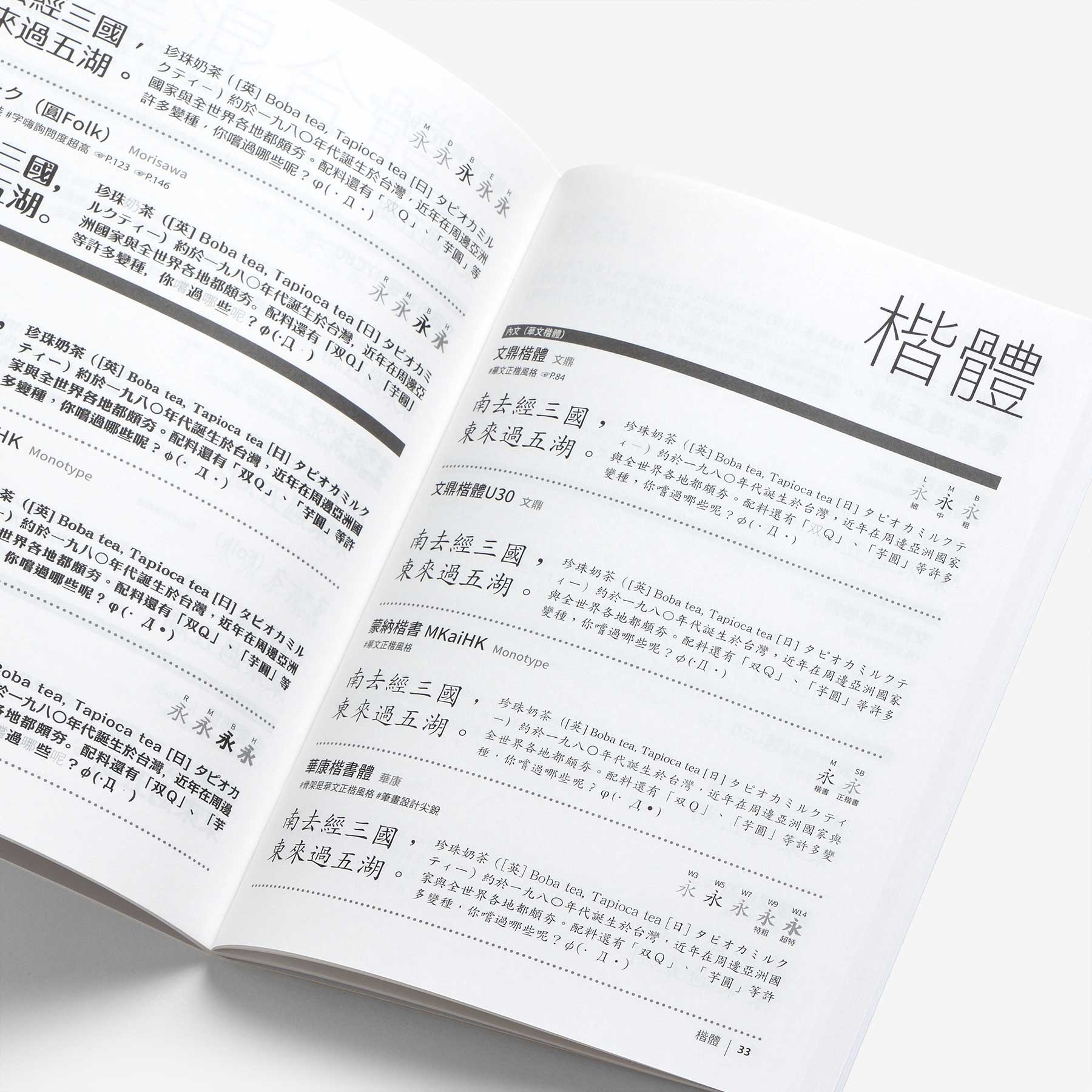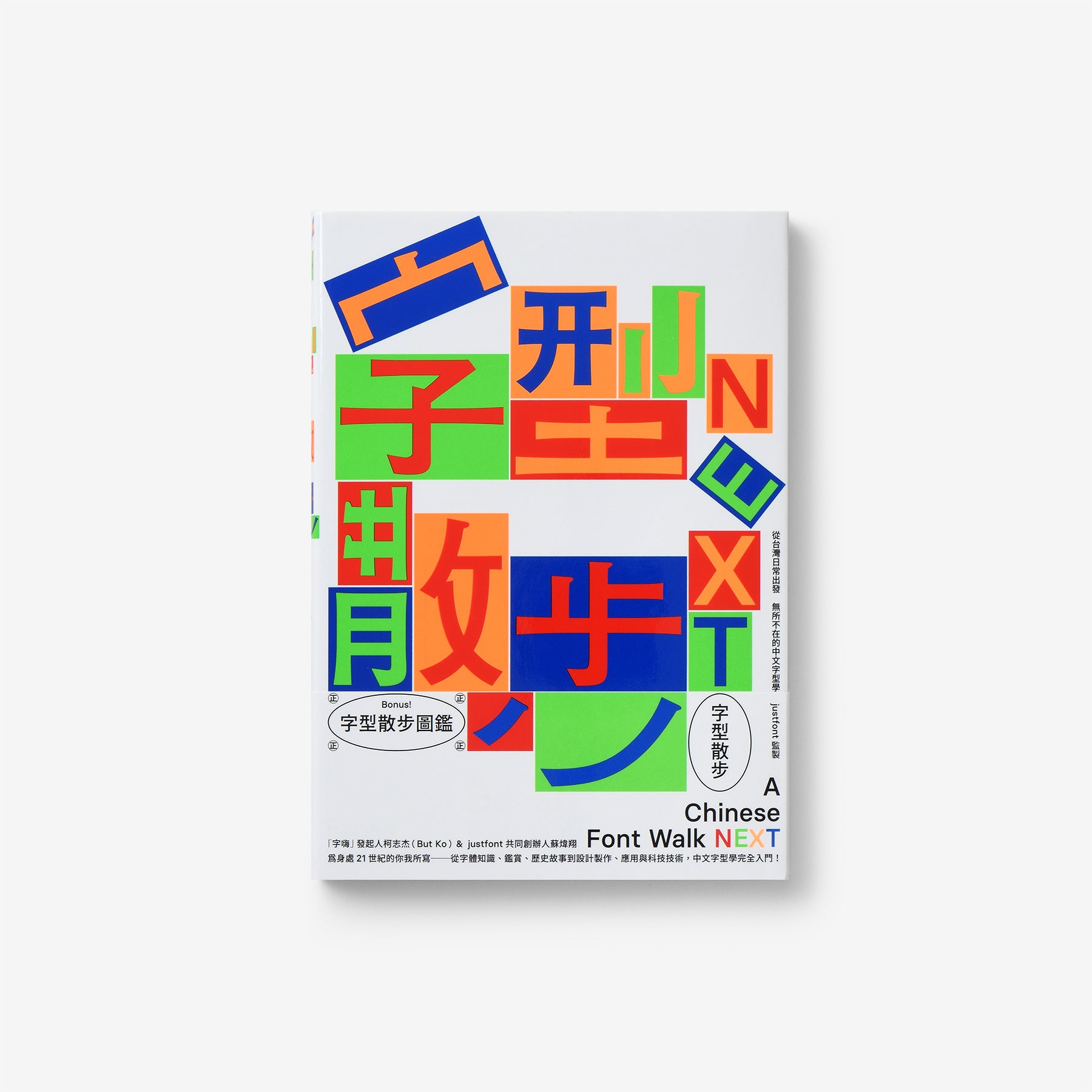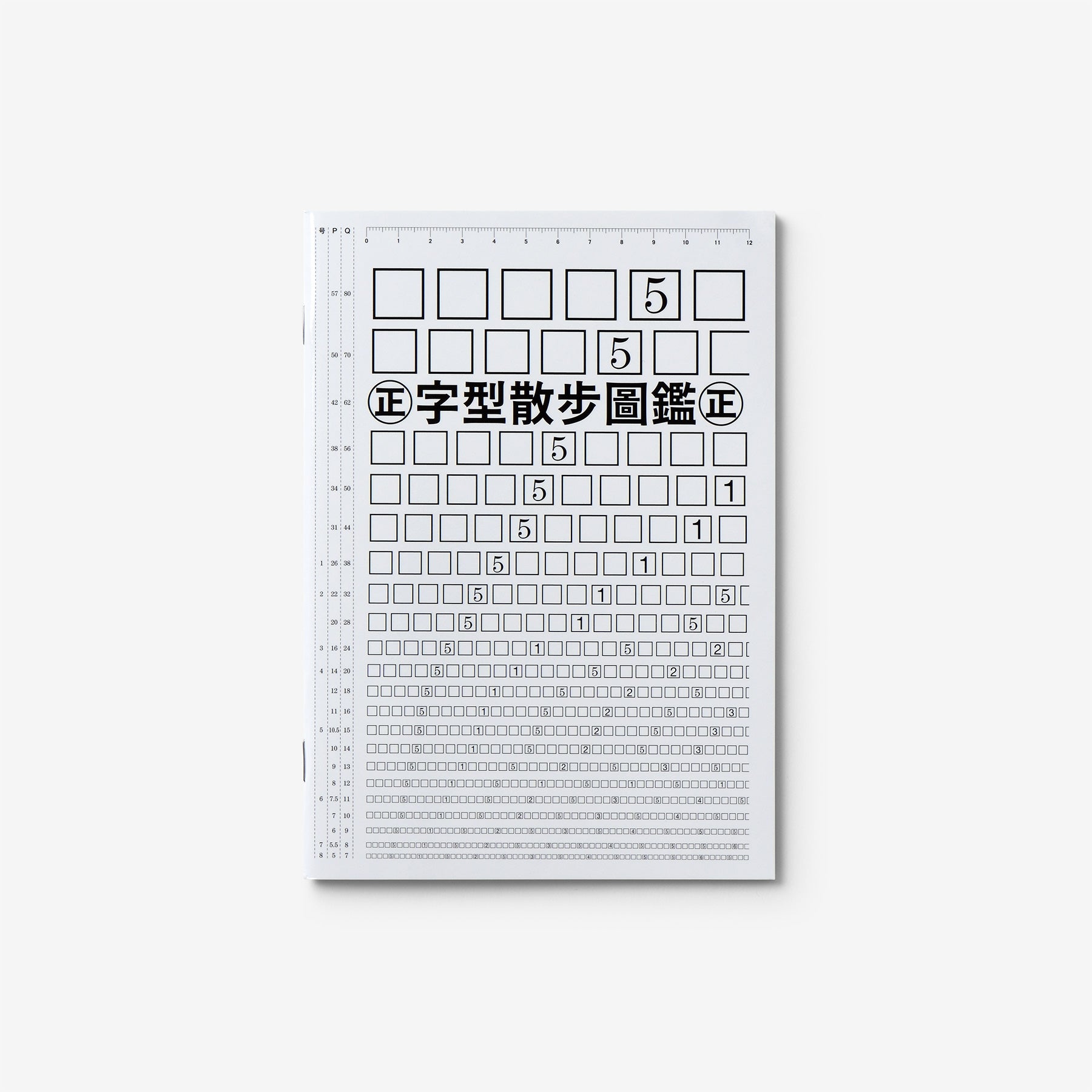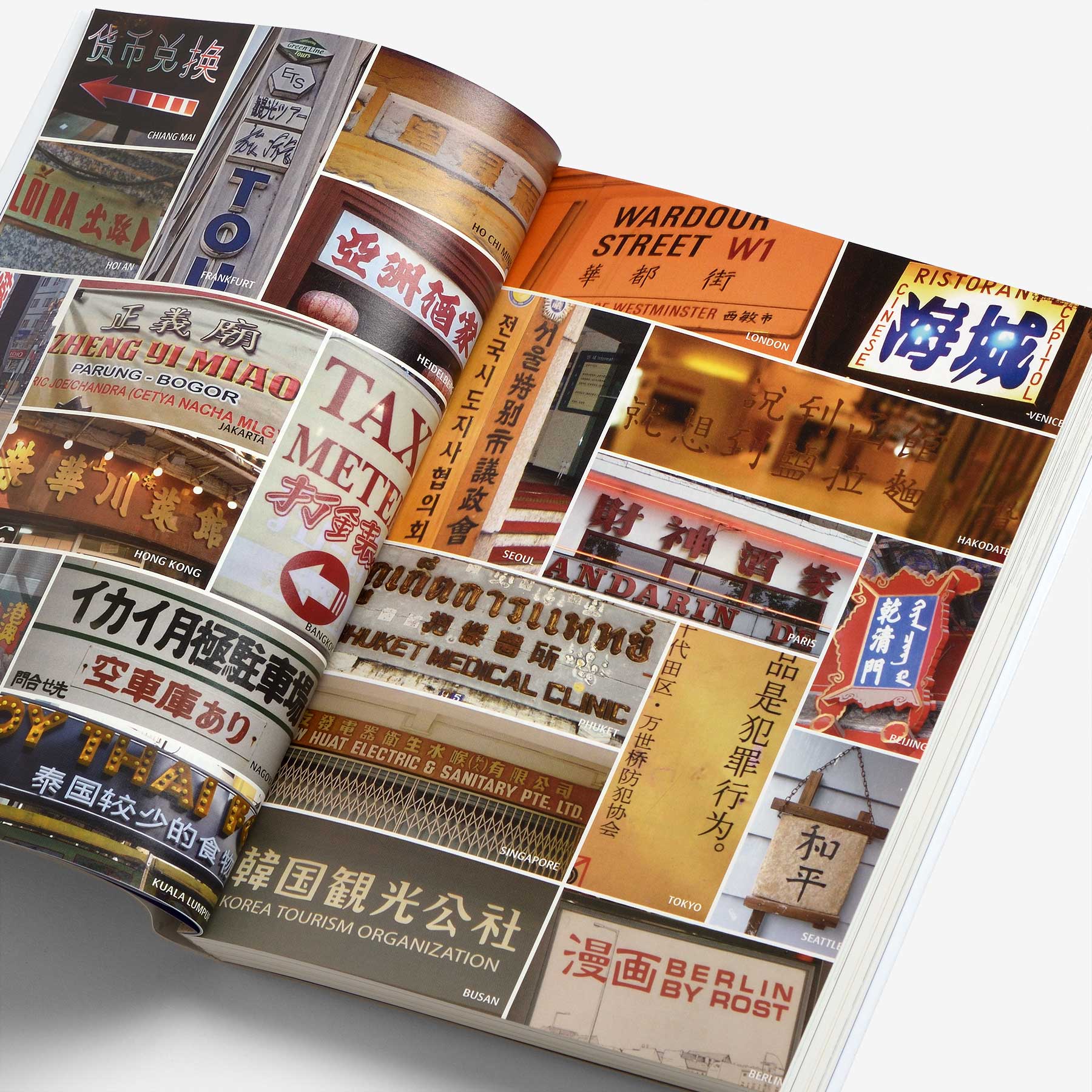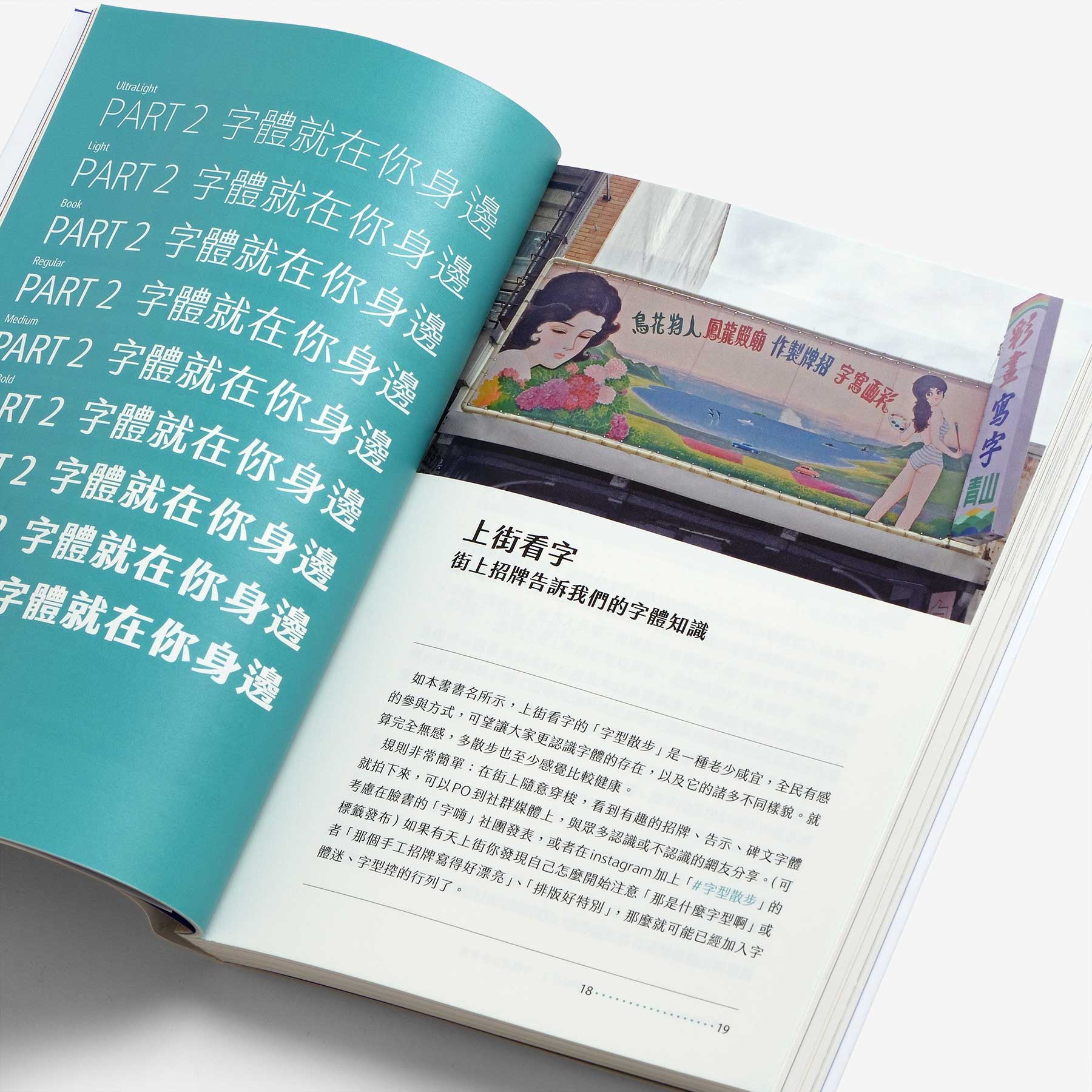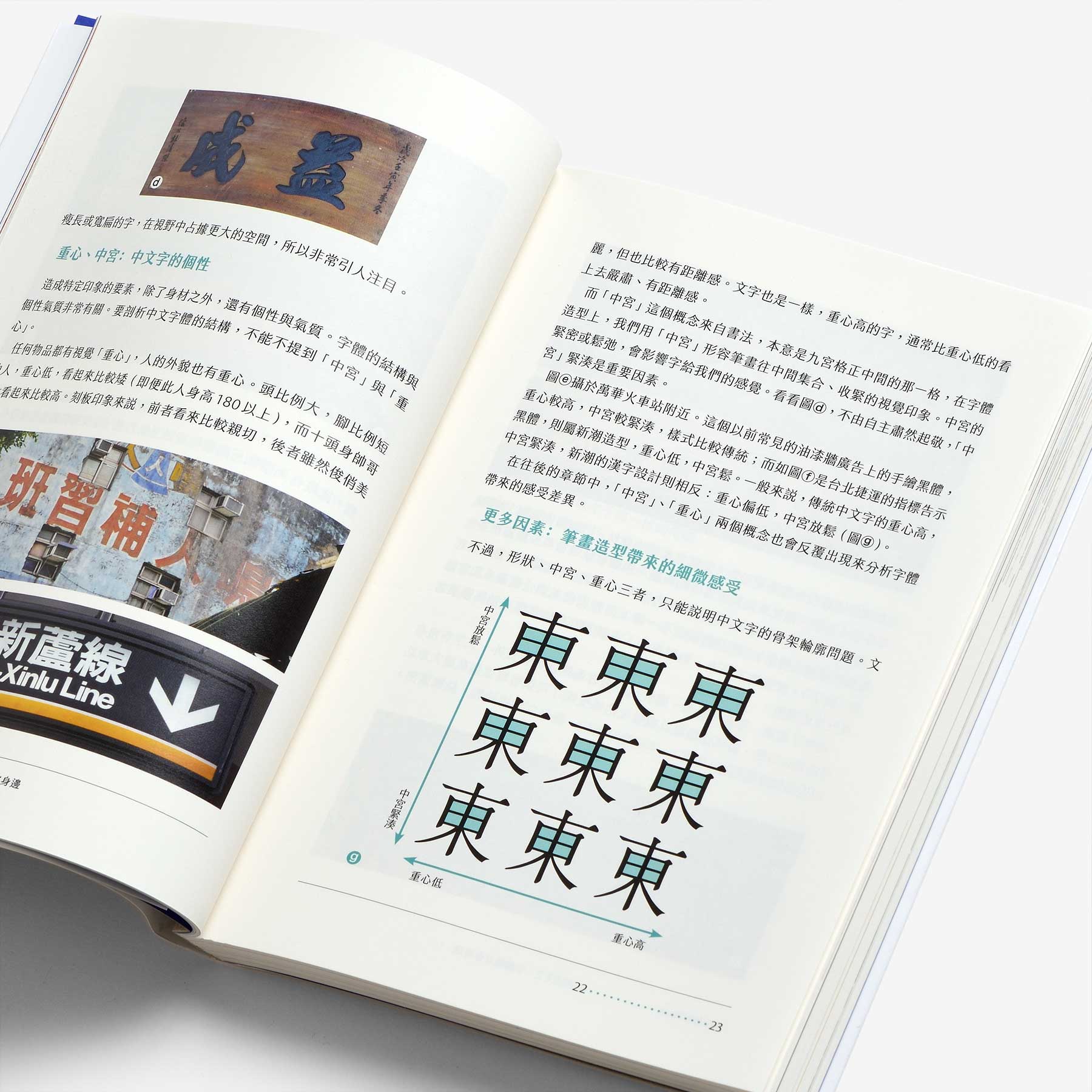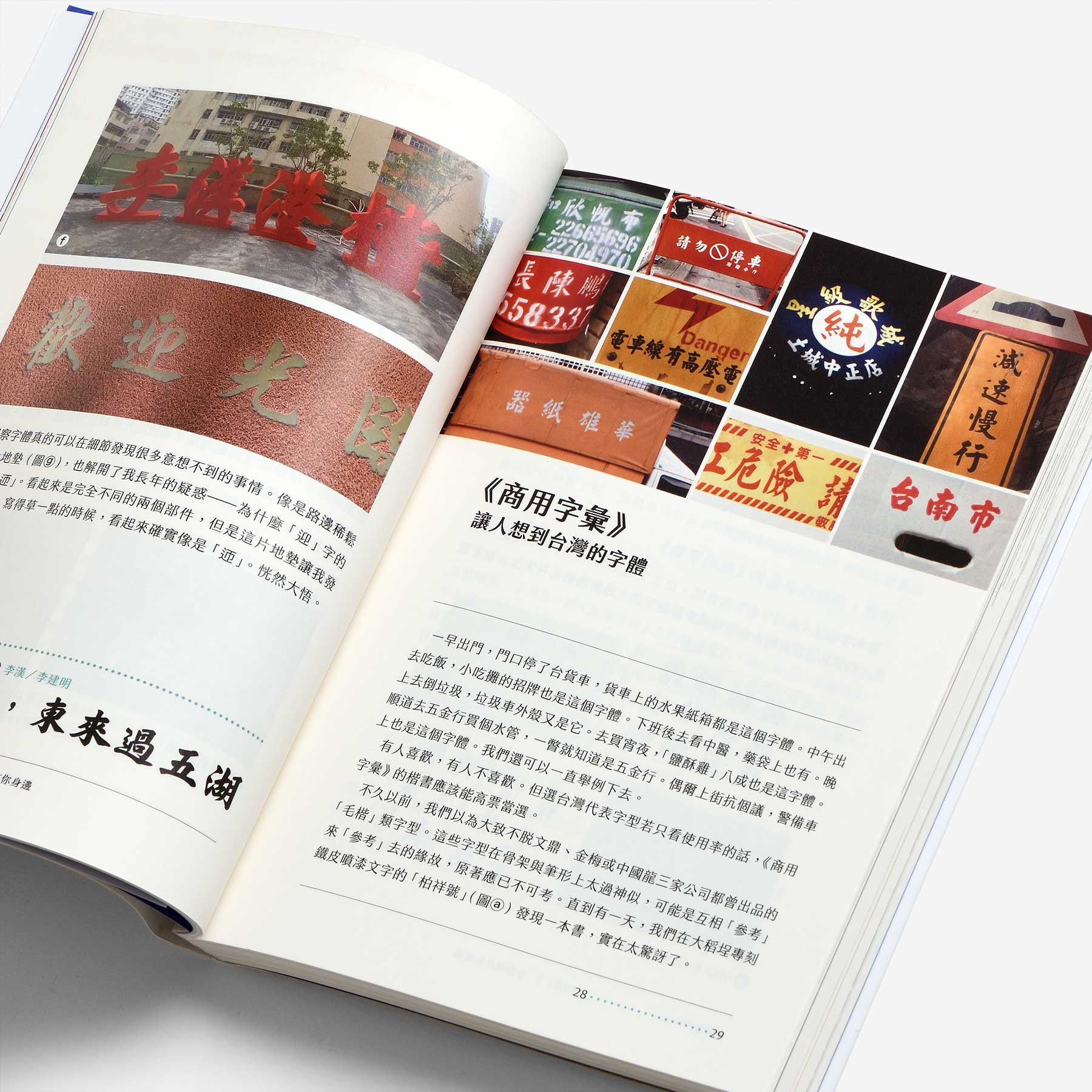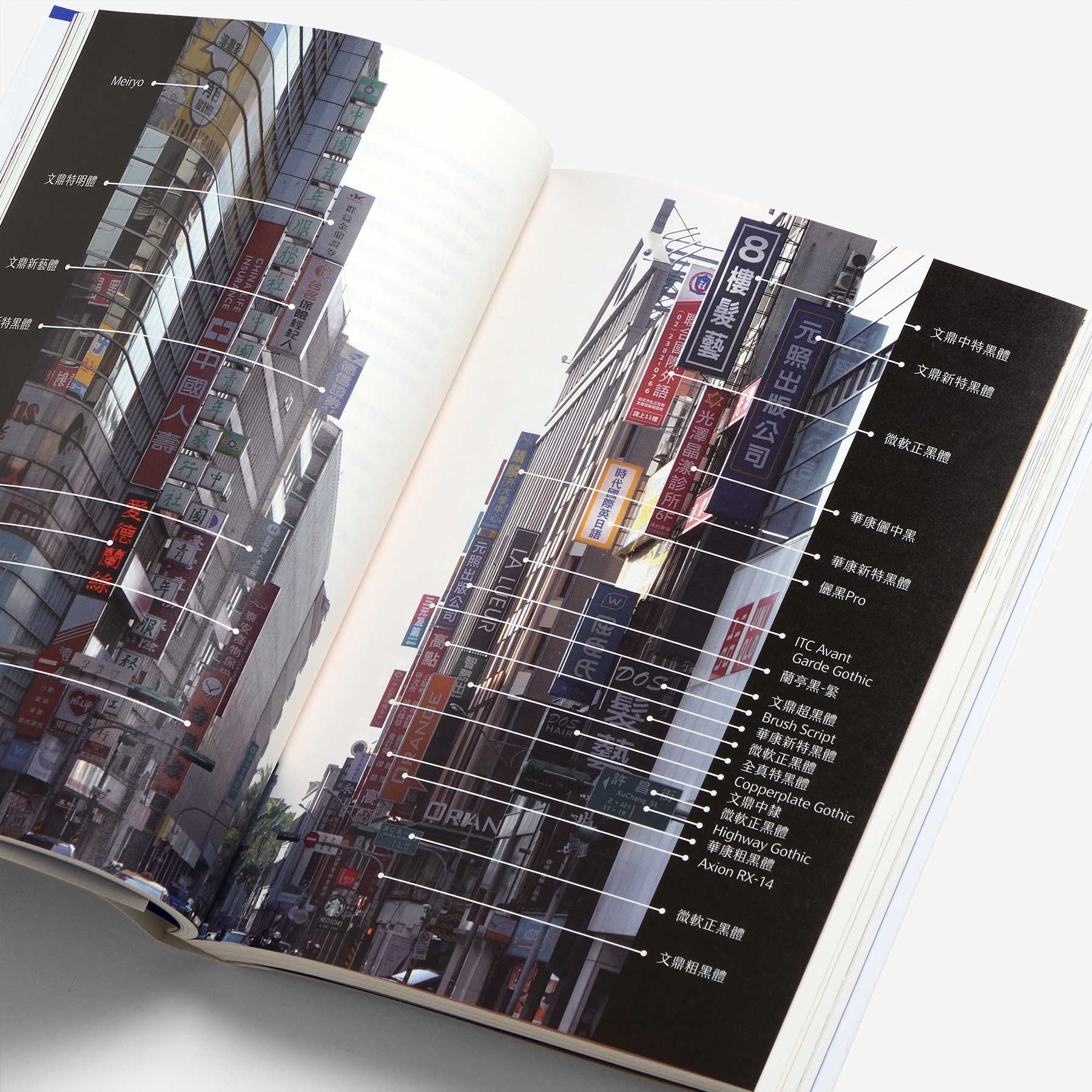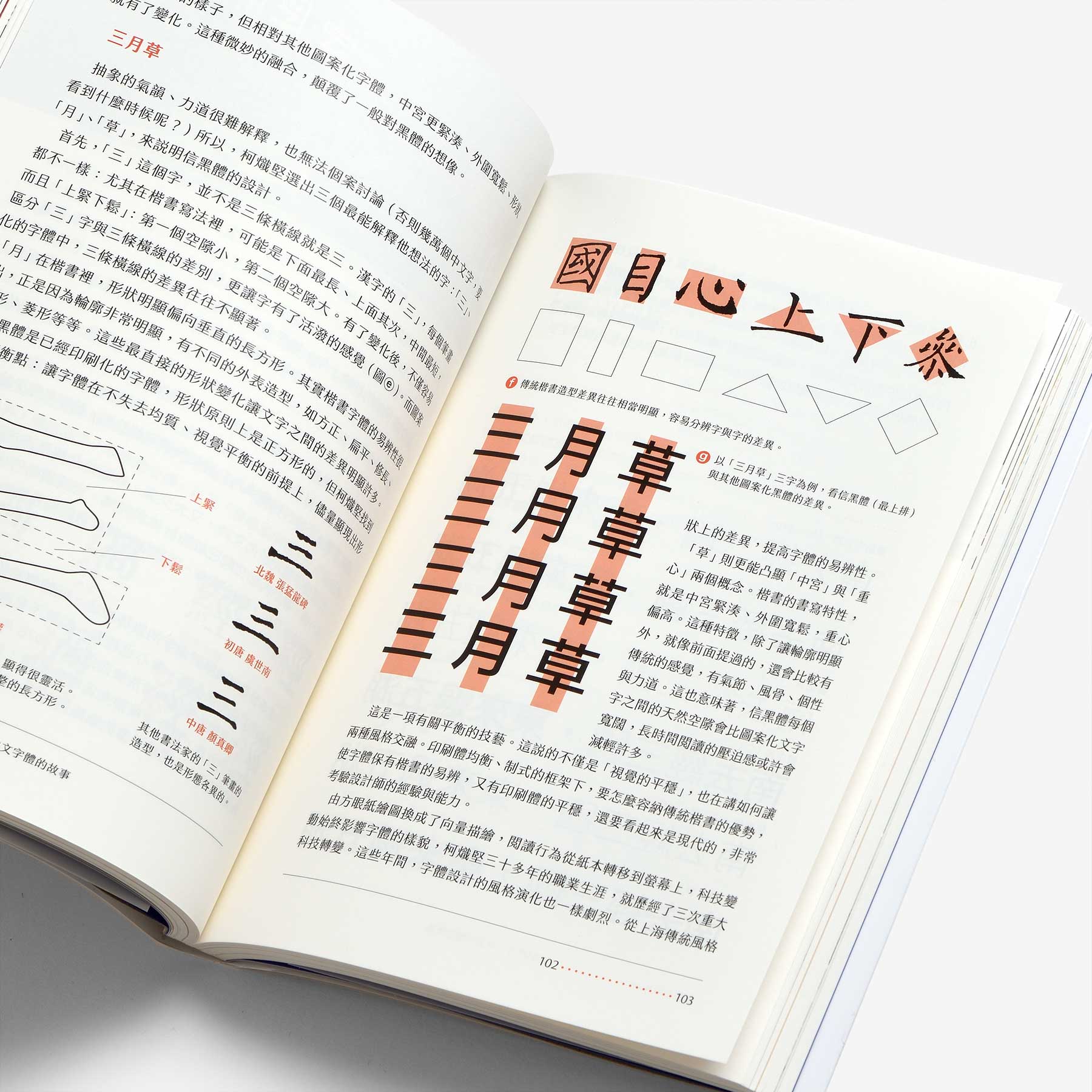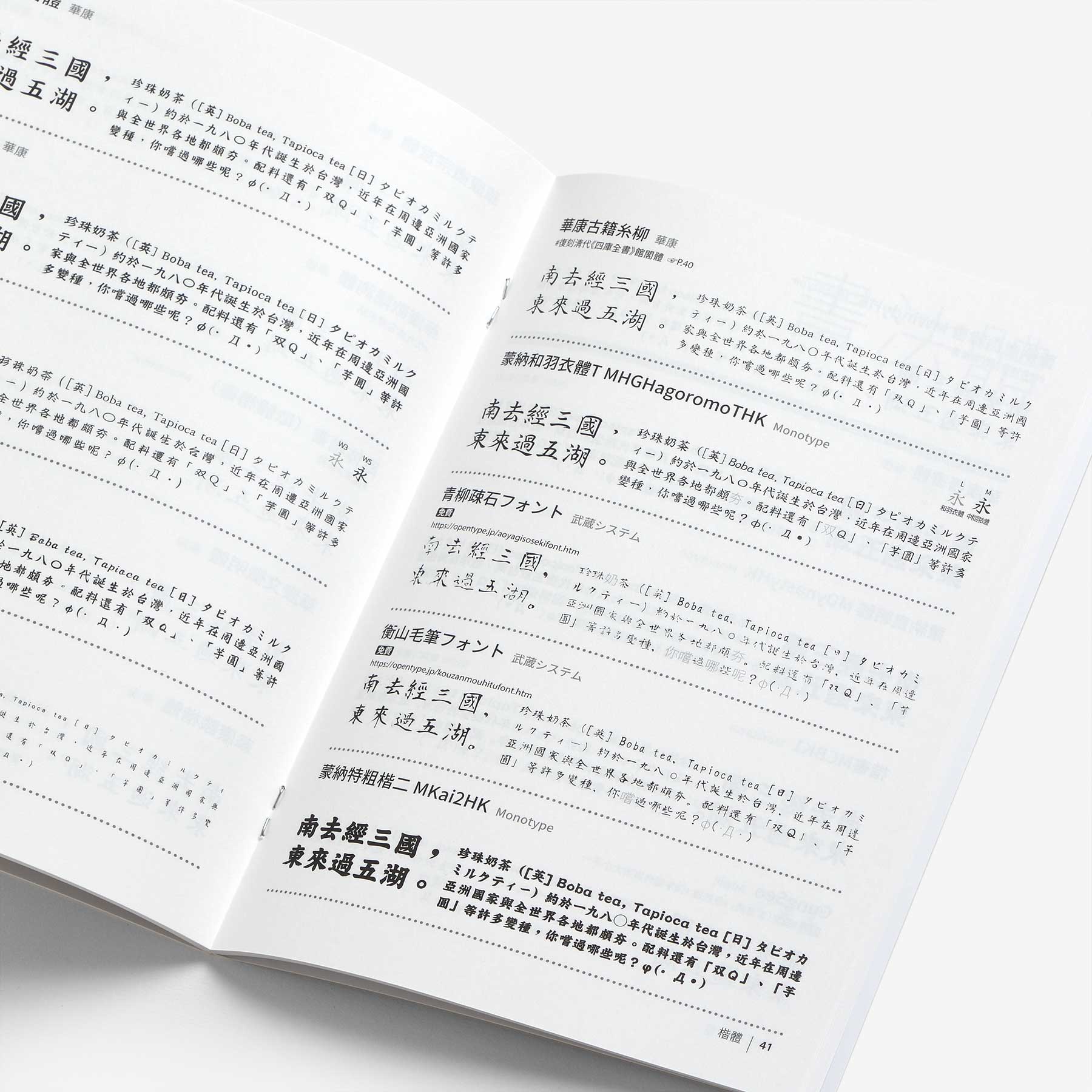
字型散歩 Next
2014年に台湾で出版された「字型散歩」が、過去5年の変化と研究を合わせ、「字型散步 Next」として漢字の知識や歴史、技術、デザインなどを紹介しています。漢字の優れた入門書であり、漢字を理解するためのガイドとなっています。台湾のグラフィックデザイナー、王志弘(Wang Zhi-Hong)がブックデザインを手がけました。
一般的な中国語フォントを参照するのに便利な「字型散歩図鑑」が付属しています。オープンソースの無料フォントなど、360以上のフォントが含まれています。